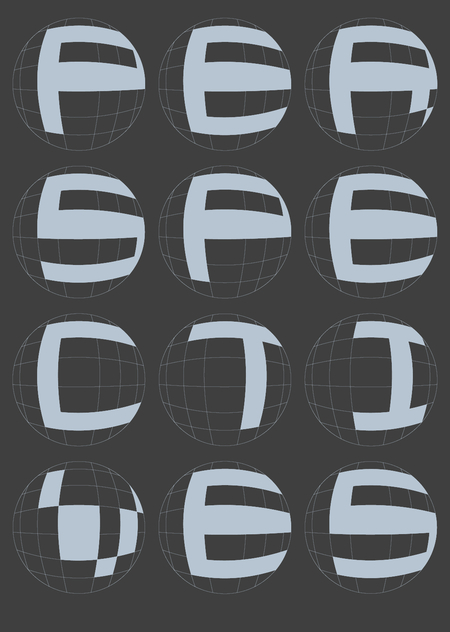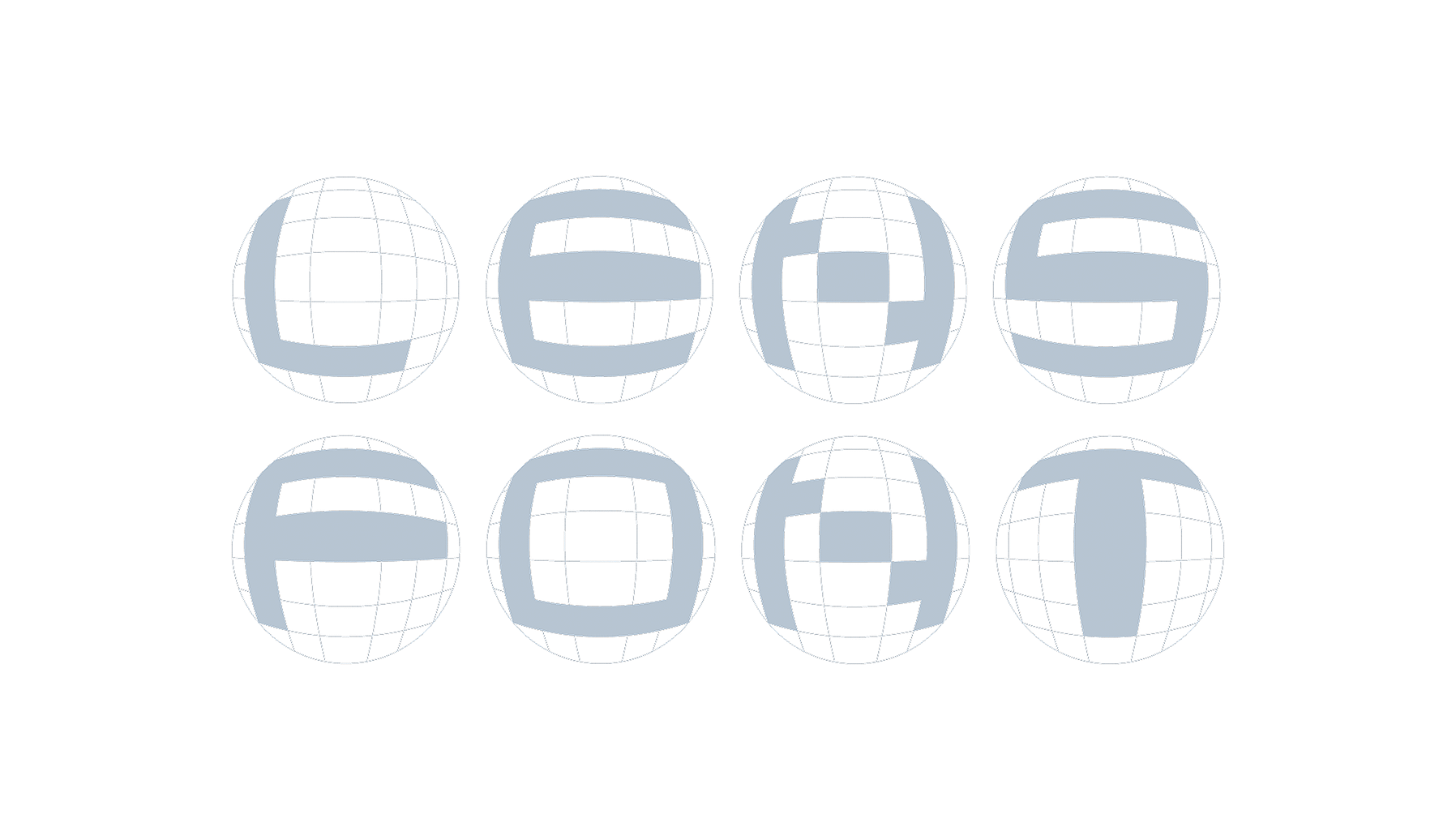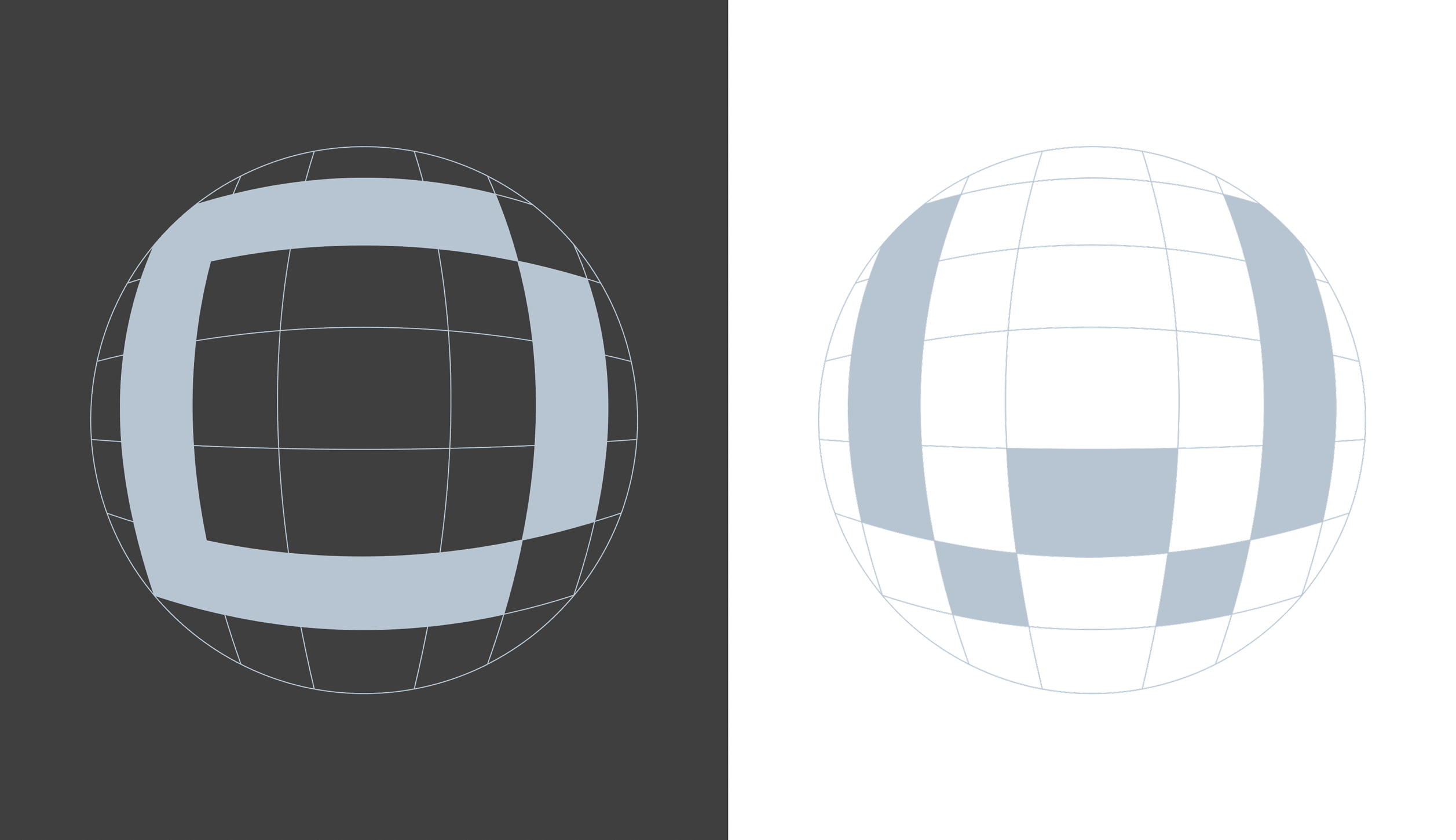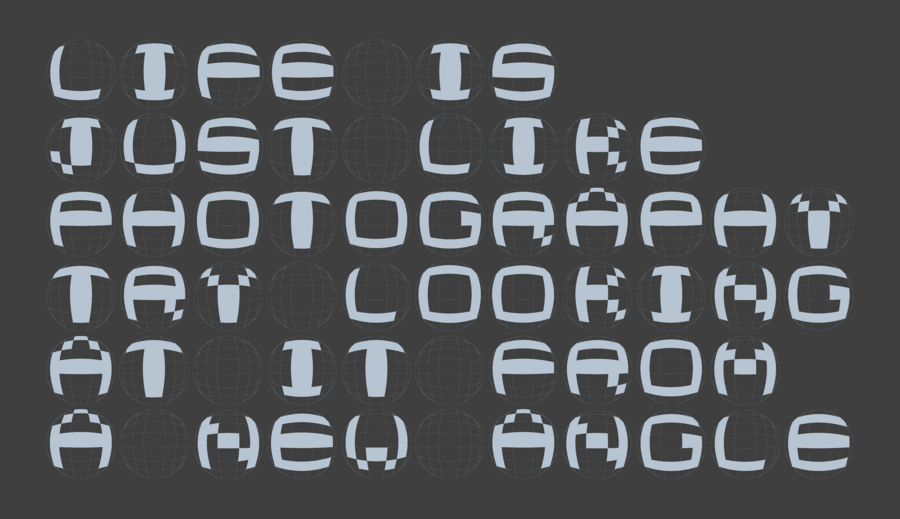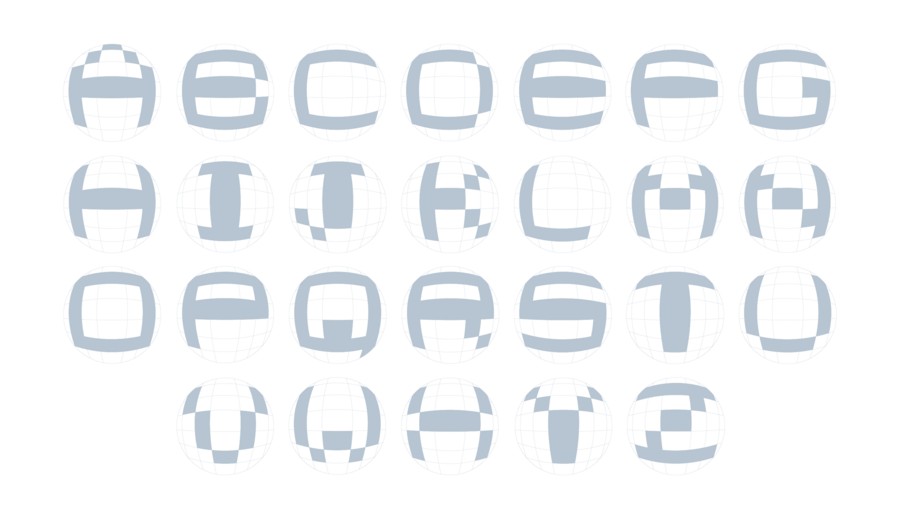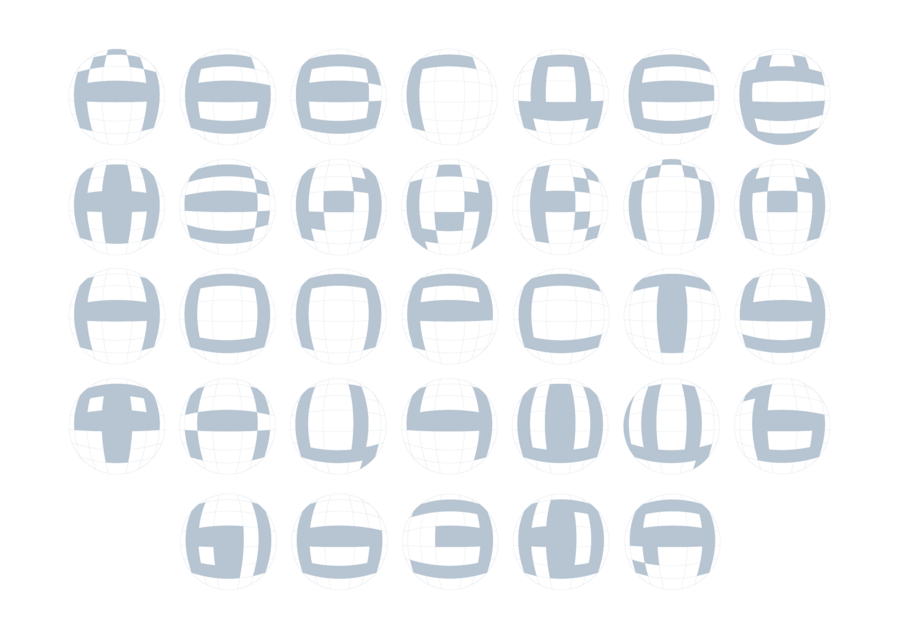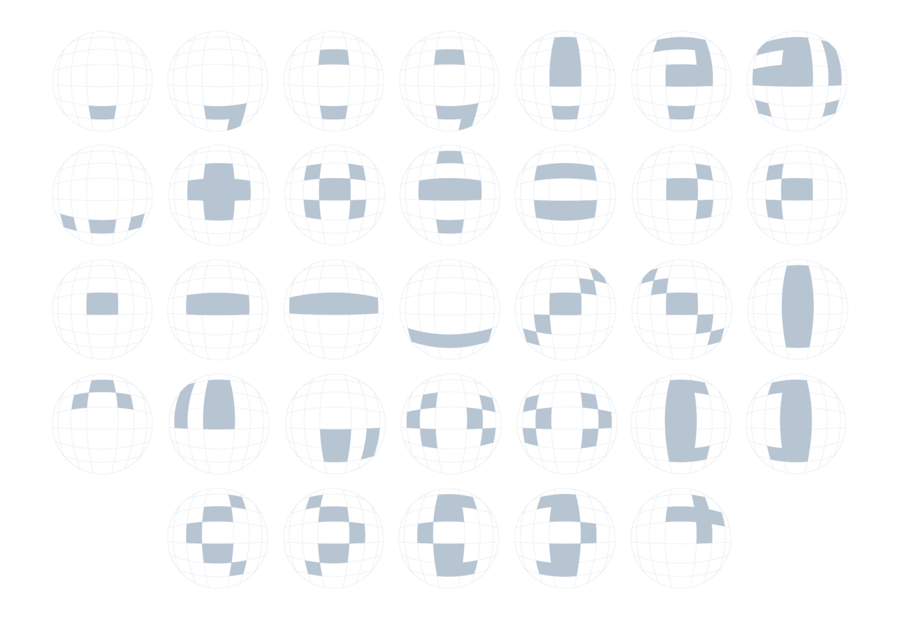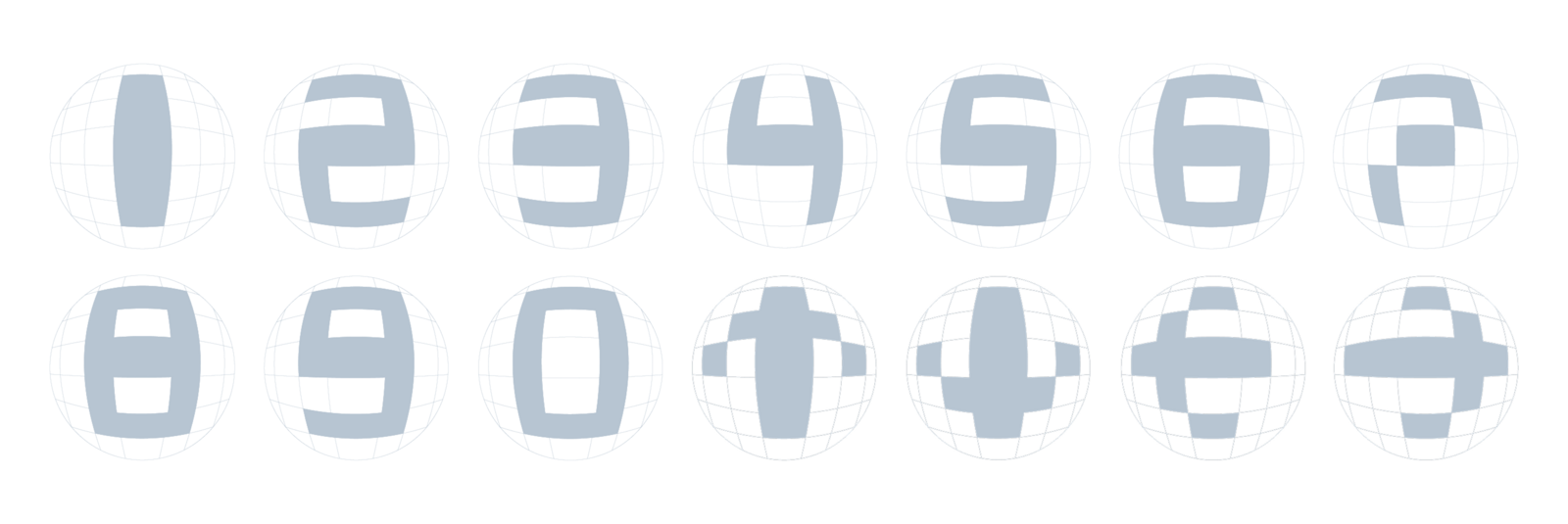
Айдентика фотовыставки Perspectives
Lens Font — шрифт, вдохновлённый выпуклой перспективой линзы фотоаппарата
В качестве айдентики для выставки буквы и символы могут перемещаться по сетке линзы, изменяясь в перспективе
Perspectives — большая фотовыставка, посвящённая теме перспективы в фотографии. Её айдентика основывается на шрифте Lens Font, вдохновлённом выпуклыми линзами широкоугольных объективов